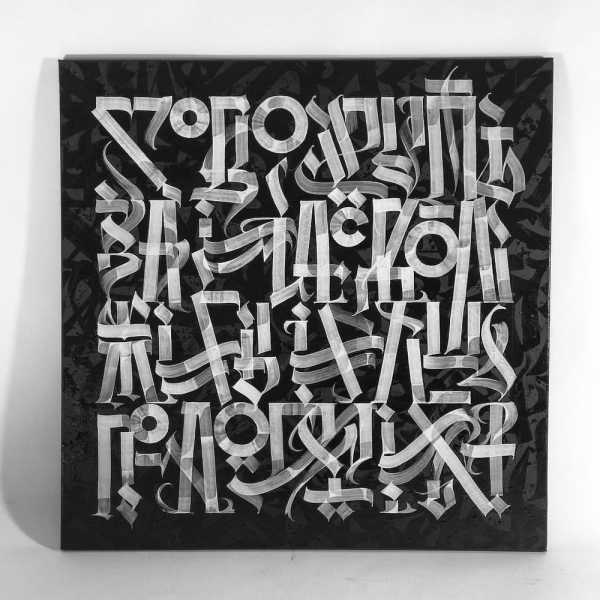
Покрас Лампас: творческий путь
Покрас Лампас (Pokras Lampas) — успешный иллюстратор, графический дизайнер и стрит-арт художник (каллиграфия). Творческий путь Покрас Лампас начался в 2005 году, когда Арсений, именно так зовут художника, заинтересовался граффити. Коллега и товарищ Андрей Анте познакомил его с миром граффити (оформления, качественные работы и вдохновение). При освоении новых техник перешел на маркеры. Его проекты отличают оригинальная каллиграфия и качественный леттеринг. Поэтому на проработку шрифтов к каждому проекту уходит много времени. Все эти навыки Покрас Лампас изучал самостоятельно. На данный момент Арсений проживает в Санкт-Петербурге, но его творчество становится известным в сотни городах по всему миру.
Каллиграфия на девушках
Покрас Лампас получил всеобщую известность благодаря проекту «Calligraphy on girls». Идея «расписывать» тело родилась спонтанно и вылилась в целую серию работ. Кроме гармоничного «вписывания» шрифтов на тело, он создает масштабные росписи на стенах и целые серии рисунков на холстах. Художнику нравится реализовывать нестандартные проекты.
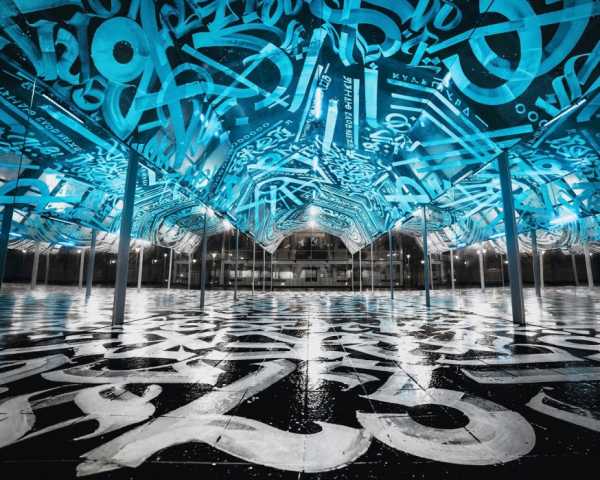
арт-объект в туннеле Ã Т Р И У М А
Его потрясающая роспись арки в Екатеринбурге выполнена так, что закрасить её другими рисунками невозможно. Поэтому она стала своего рода элементом ориентира в городе. В этой росписи он вшил фразу «All Your Walls Are Belong To Us» (Все ваши стены принадлежат нам), которая читается только в ультрафиолете — ночью с направленным потоком света (фонарь или лампа). На работу ушло около недели. Она была сложной, потому что расписывать пришлось все поверхности — трубы, столбы, кондиционеры, пол и потолок.
Постоянное общение и встречи позволяют Pokras Lampas делиться информацией, перенимать знания, анализировать их и использовать в своём творчестве.
Покрас Лампас постоянно путешествует и пребывает в творческом процессе — разрабатывает принты и логотипы, эскизы к новым тату, экспериментирует, тренирует стили, занимается оформлением, проводит воркшопы и мастер-классы, участвует в фестивалях, ездит по городам, сотрудничает с крупными автомобильными брендами Германии и Чехии. Его лекции настолько интересны, что многие после них начинают серьёзно заниматься каллиграфией.
«Чтобы создать что-то новое, нужно много экспериментов» – Ярмарка Мастеров
Арсений Пыженков, работающий под псевдонимом Покрас Лампас, — молодой петербургский каллиграф, основатель стиля «каллиграфутуризм» (направление в современной каллиграфии), создает удивительные вещи, совмещая каллиграфию, стрит-арт и перфоманс.
Экспериментируя с формами и возможностями шрифтов различных алфавитов, Покрас создает масштабные каллиграфические композиции в городской среде и интерьере. Каждая работа со шрифтами заключает в себе смысл — цитаты великих художников, дизайнеров и собственные философские поиски. Современная каллиграфия должна работать как яркий, запоминающийся, оригинальный образ — это послание создатель каллиграфутуризма с успехом реализует в своих произведениях.
C Õ C T P Ã Д Å H И Ę / Ē M P Ã T H Ÿ
«Продолжаю эксперименты по смешиванию арабских и кирилличских букв. Один из главных холстов выставки «Calligrafuturism. Chapter 1.0».
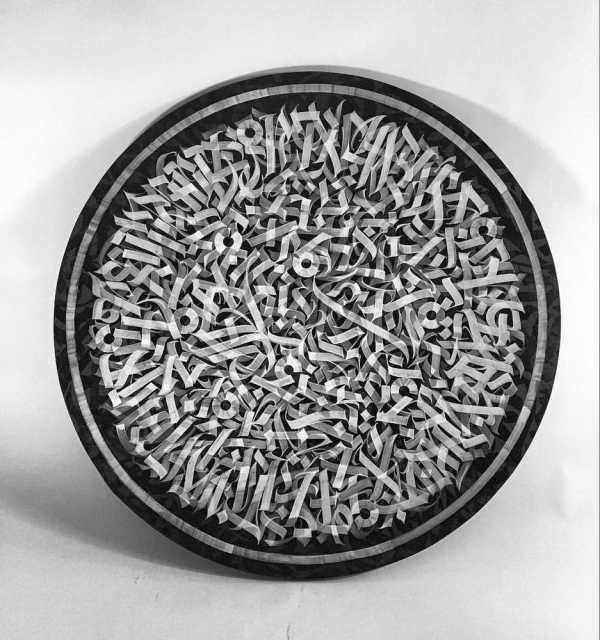
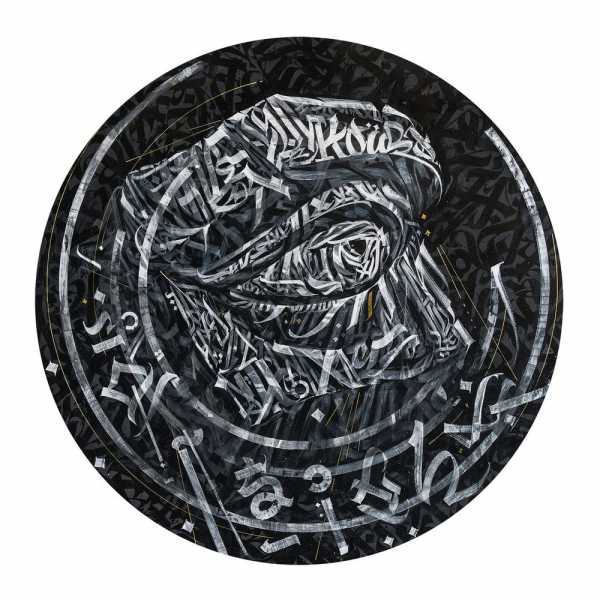
Ï Ñ S —’ G H T̅ / Insight.
«Основанная на скульптурной форме глаза Давида, эта работа посвящена моему видению букв в далёком будущем».
«Для тех, кто там что-то писал про однообразие монохромных работ — друзья, конечно я умею делать много разных вещей. Другое дело, что упрощая цвета, сильнее фокусируешься на формах, что очень важно для самообразования».
«Одна из самых больших проблем начинающих современных художников и дизайнеров в том, что никто не хочет выйти за рамки комфортных условий, задач и проектов.
Лучше сделайте сотню ошибок, пробуя новые инструменты, краски, масштабы, техники и так далее, зато спустя время это создаст вам бесценный запас опыта и готовность к работе над новым технически нестандартным проектам.
Я часто создаю абстрактные на первый взгляд вещи, но их ценность в том, что изначально это стройные, проработанные композиции, которые потом разрушаются и теряют прежние формы».
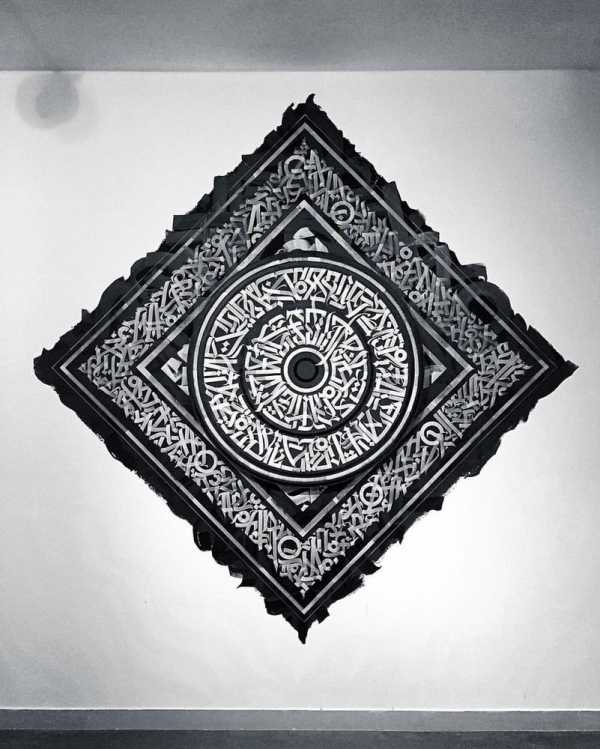
«Для того чтобы создать что-то новое, нужно много экспериментов… Когда я вношу хаос, я перед этим делаю огромное количество работ для того, чтобы найти форму и порядок, и даже при хаотичности деталей общая композиция имеет четкую ритмику, баланс светлого и темного, правильно расставленные акценты».
На фото ниже — экспонаты выставки «Calligrafuturism. Chapter 1.0», Дубаи.
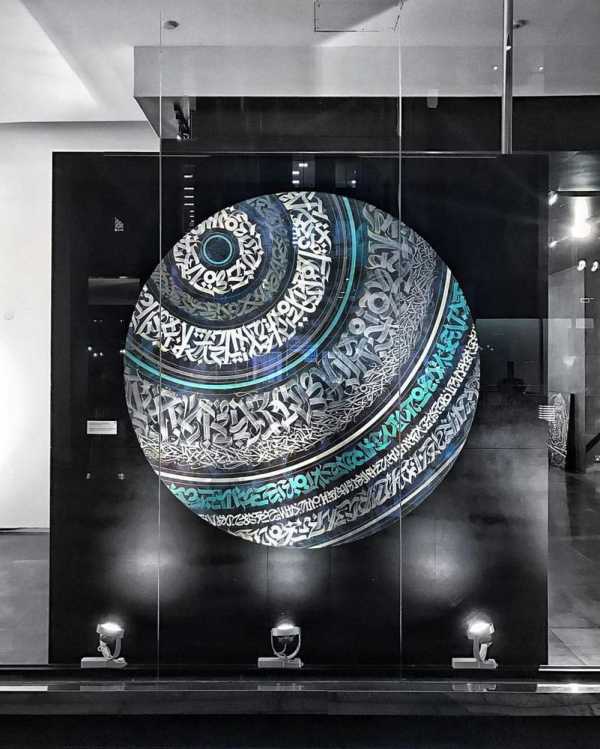
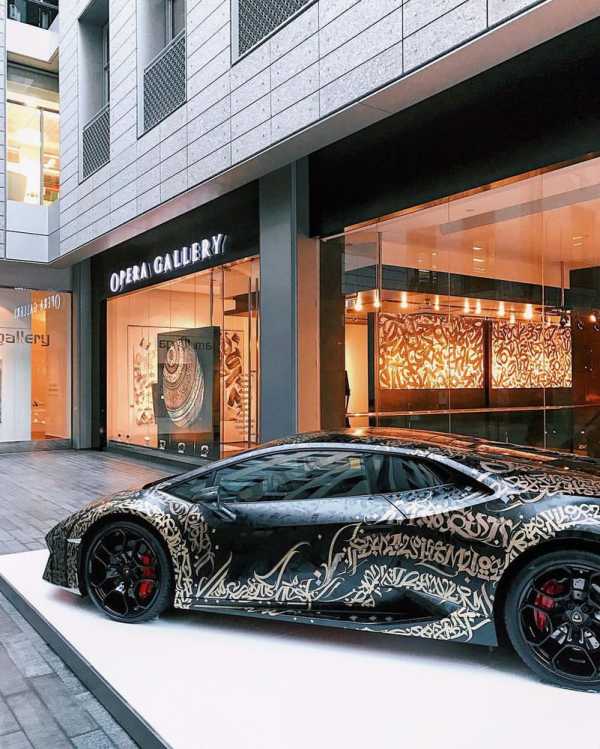
На фото ниже — масштабные стрит-арт каллиграфические композиции.
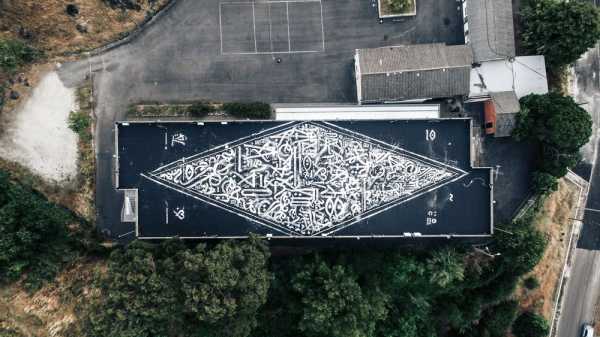
1200 кв. метров каллиграфии на крыше в Португалии.
«Этим летом в городе Луре рядом с Лиссабоном я расписал новую крышу, продолжая свои эксперименты с огромными буквами (некоторые из них были больше трех метров в длину). Следуя своей концепции каллиграфутуризма, я написал свои размышления о том, что когда-нибудь мы все поднимемся над своими районами, откроя глаза, сердце и разум. И включил в роспись соответствующие символы-буквы».